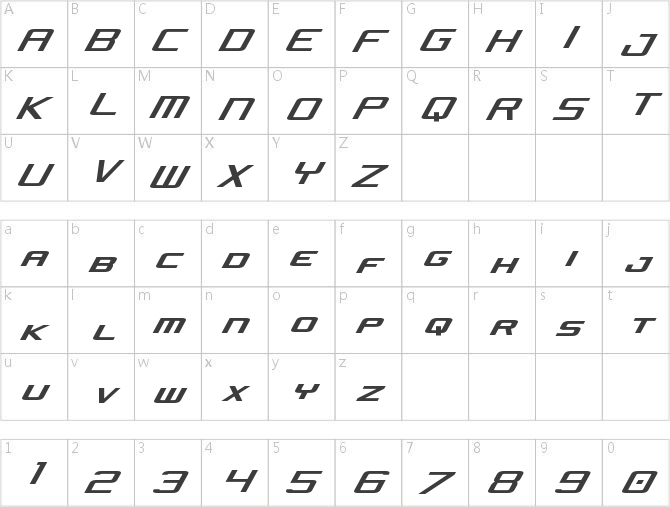
Concielian Jet Condensed Italic 詳情頁(yè)
Concielian Jet Condensed Italic字體字庫(kù)是一款讓人賞心悅目、百看不厭的英文字體,適合各類(lèi)廣告和產(chǎn)品包裝設(shè)計(jì)應(yīng)用,字體大小0.03MB,格式為ttf字體,上傳用戶(hù)是快霸中國(guó),作者/版權(quán)方為未知